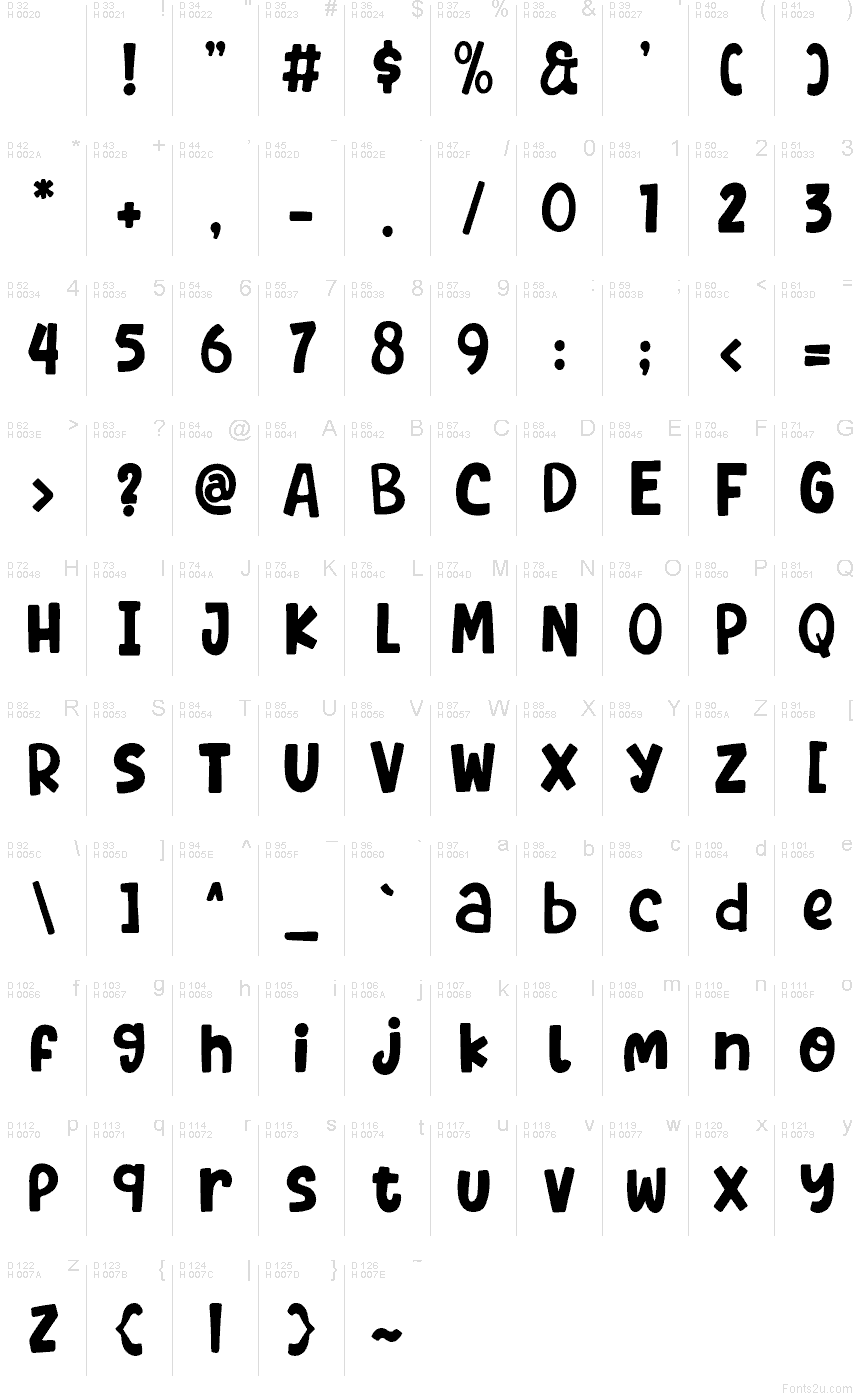
Letter Magic de Dm Letter Studio es una tipografía de estilo cartoon gratuita, con letras suaves e infladas y un toque amigable y artesanal. Sus formas redondeadas se sienten sólidas y sencillas, con curvas cerradas y remates cortos que le dan a la tipografía una energía lúdica ideal para títulos infantiles, sin perder la claridad.
Encaja perfectamente en empaques, invitaciones de cumpleaños, carteles escolares, miniaturas de YouTube y branding alegre donde buscas una fuente gratuita que se vea grande, cálida y desenfadada. Úsala en titulares cortos, títulos de presentación o logotipos, ya que sus curvas gruesas y su ritmo juguetón hablan por sí solos.